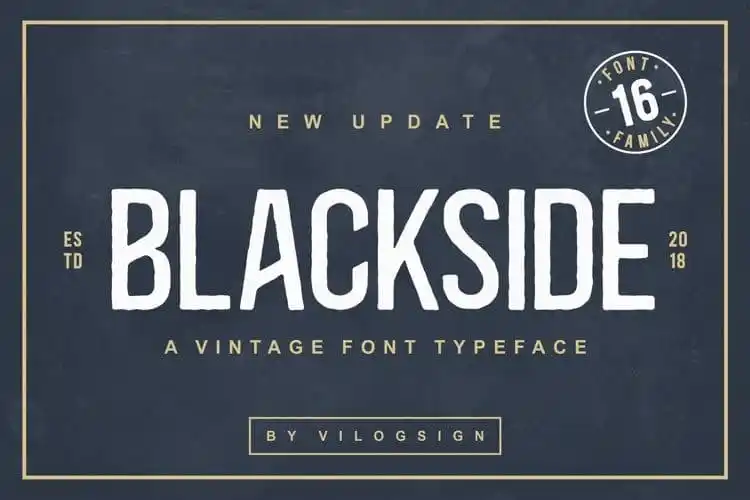
Blackside Display Font Family – Fonte Grátis
Blackside Display Font Family
A Blackside Display Font é uma tipografia vintage única criada por Vilogsign. Ela carrega um estilo vintage distintivo e uma personalidade forte. Desenvolvida com cuidado, esta fonte possui 16 caracteres que ganham um toque de grunge para adquirir o visual vintage perfeito. Perfeita para seus projetos, ela é ideal para criar designs elegantes e autênticos. Seja para logotipos, headings ou qualquer outra aplicação onde uma pitada vintage vai fazer toda a diferença, essa fonte certamente será sua escolha.